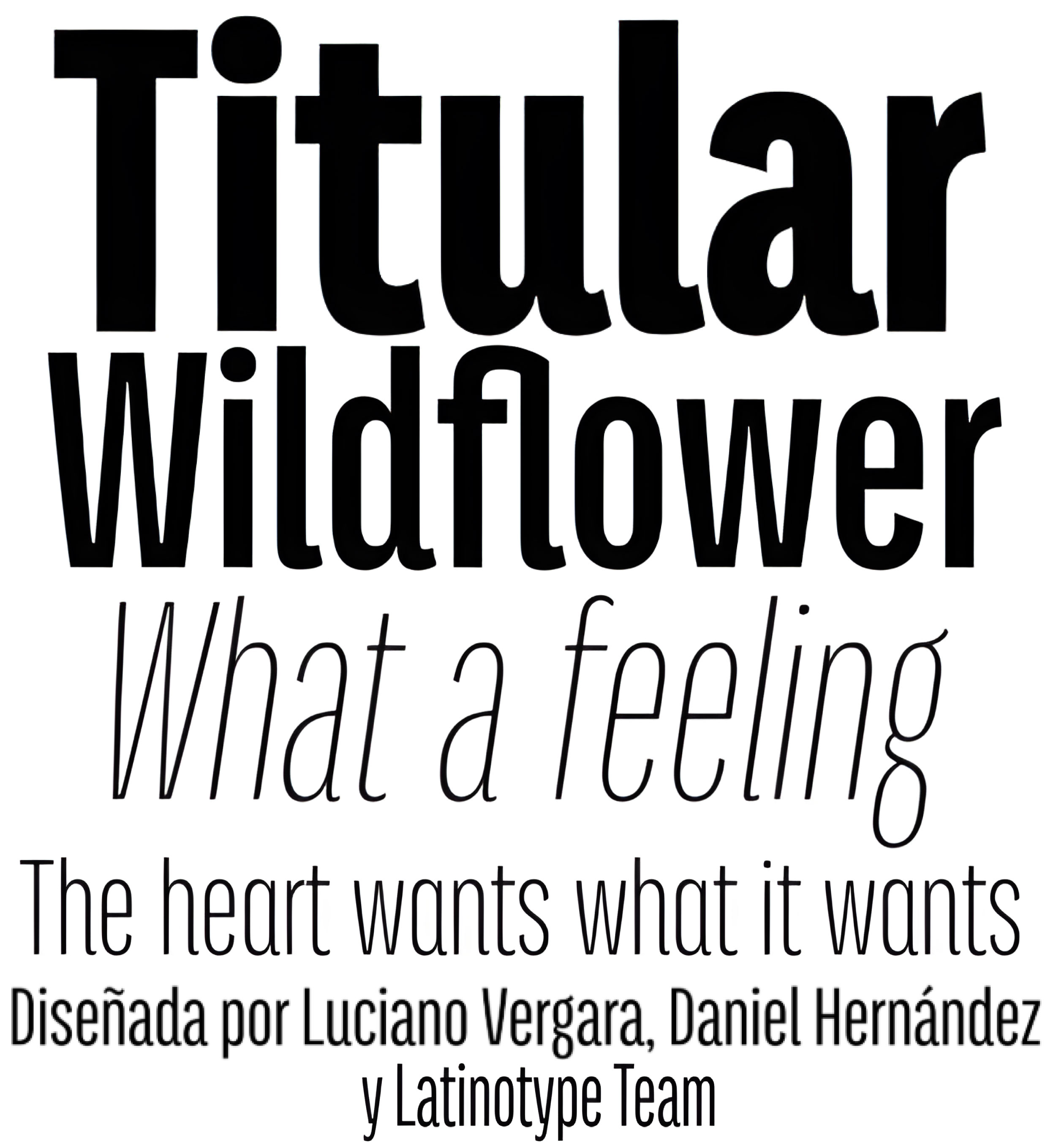
| Año | 2015 |
| Créditos | Luciano Vergara, Daniel Hernández, Latinotype Team |
| Descripción | Titular es un tipo de letra Sans Serif condensado que funciona bien con titulares, subtítulos, periódicos, revistas, así como con logotipos, marcas y carteles. Este tipo de letra revive el espíritu de las antiguas Woodtypes, pero añadiendo un sabor contemporáneo y un condimento latinoamericano. La familia viene con 2 subfamilias: una regular y otra alternativa. Al igual que muchas de nuestras caras, cada subfamilia incluye 7 pesos más cursiva. Titular es un tipo de letra de Latinotype diseñado por Bruno Jara y producido y supervisado por Latinotype Team. El equipo de Latinotype está formado por: Luciano Vergara, Daniel Hernández, Bruno Jara, César Araya y Rodrigo Fuenzalida. |
| Familia(s) | Titular |
| Estilos | 28 |
| Estudio | Latinotype |